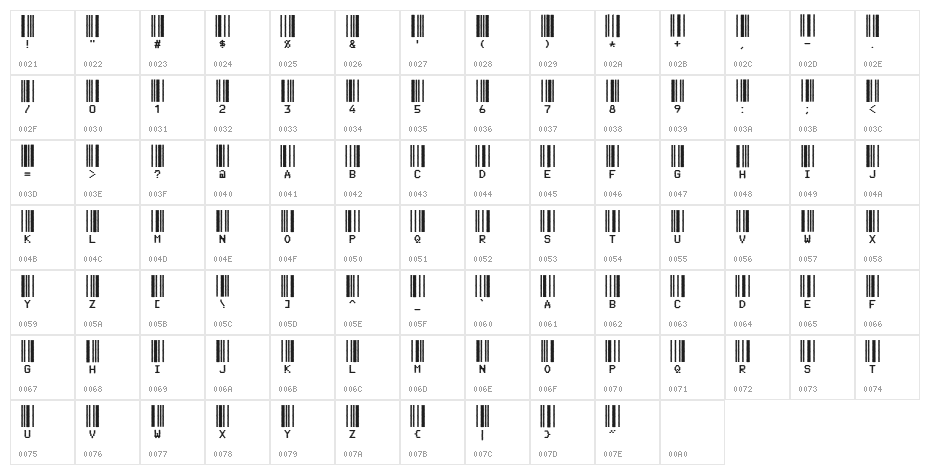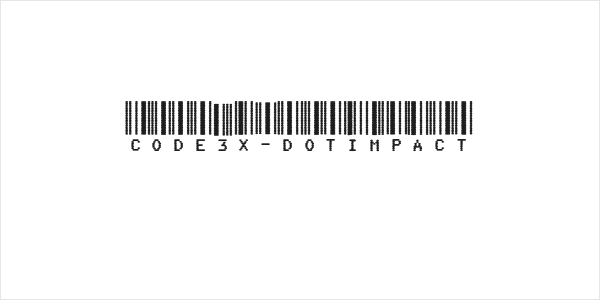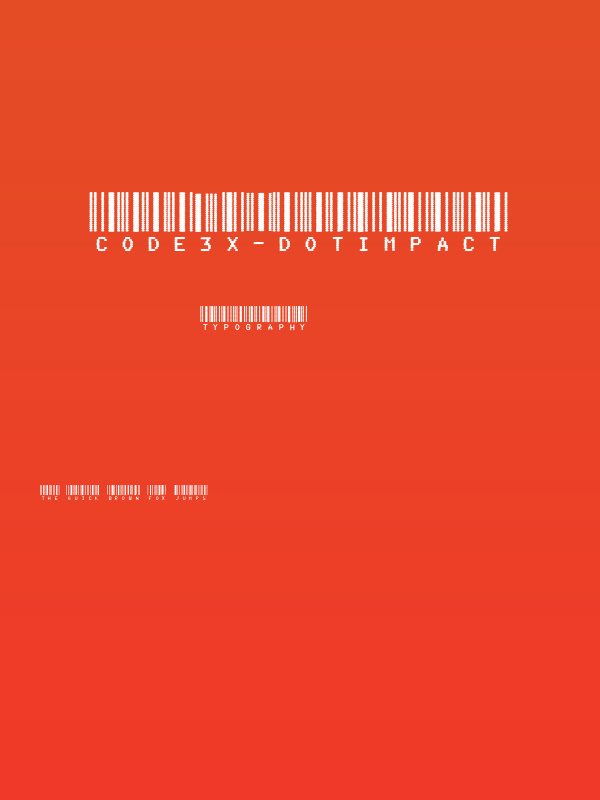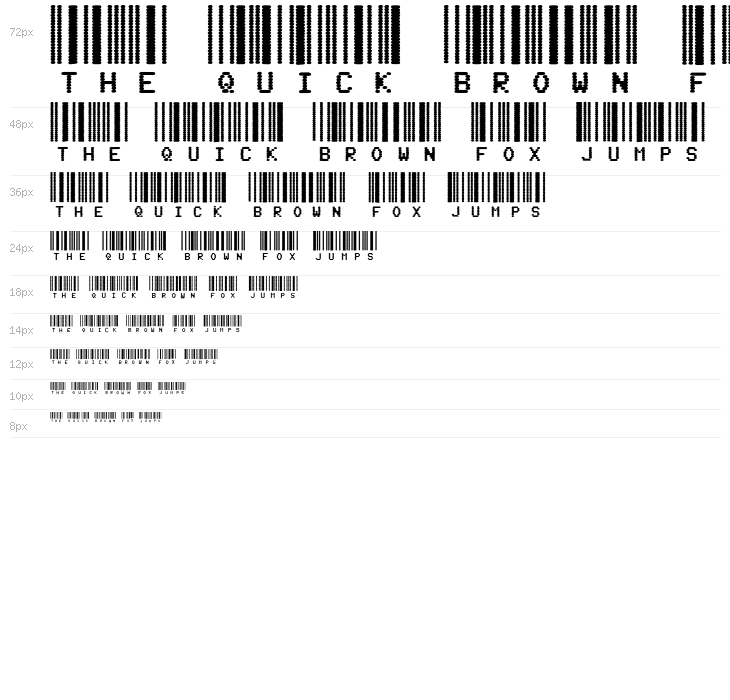
Code3X-DotImpact Font
| Stile generale | Modern, Digital, Industrial |
| Caso d'uso | Logos, Posters, Digital Art, Tech-themed Designs |
| Progetti proposti | Ideal for projects involving technology themes, digital art, industrial design, or any creative work that benefits from a futuristic or retro digital look. |